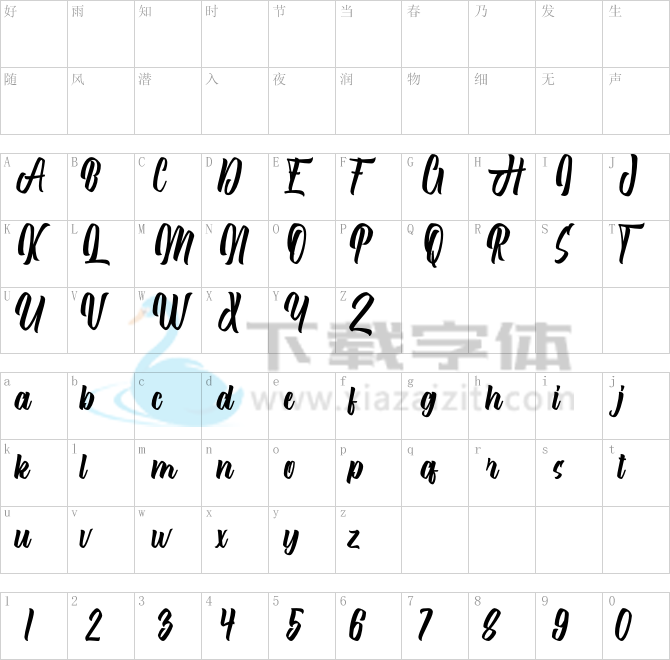
After Breaking.otf字体下载
After Breaking.otf字体下载,这款字体结构工整、笔画清晰,兼顾美观与易读性,适用于标题、正文、海报、包装、LOGO 等多种场景。字形优雅稳定,风格百搭耐看,适配日常排版与创意设计,让文字呈现更舒适、更具质感。After Breaking.otf字体下载一笔一画,皆是细节,以均衡的比例、流畅的线条打造舒适视觉体验,字形端正大气,风格简约现代。无论是商业设计、品牌宣传还是日常排版,都能轻松驾驭,让文字更有格调与力量。After Breaking.otf字体下载字体下载。